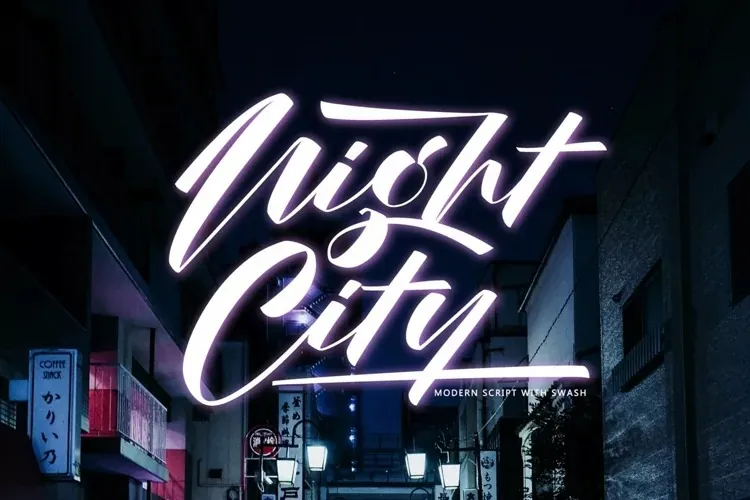
Night City Font – Fonte Grátis
Night City Font
Esta é uma fonte de script escrita à mão que proporciona um estilo pessoal e único. Ela se destaca com sua aparência esplêndida, perfeitamente adaptável a diversas idéias de design, desde cartões de convidados e cartas de gratidão até logotipos e selos para casamentos e cartas de cumprimentos. Seu charme e personalidade se destacam em qualquer aplicação onde é necessário um estilo único e autêntico, como a ilustração de uma festa nupcial ou o design de um logo empresarial. Além disso, ela também encaixa-se perfeitamente no formato ‘Night City’, criando um look urbano moderno e elegante para qualquer aplicação que precise de um toque sofisticado. A Night City Font é uma escolha ideal para designers buscando expressar a sua identidade visual de maneira única, seja em cartões de despedida ou em elementos visuais de marca.